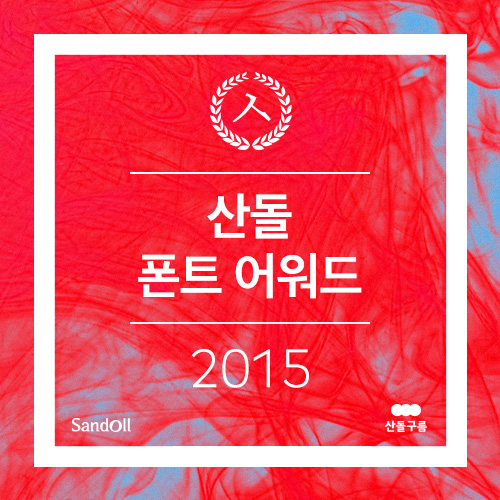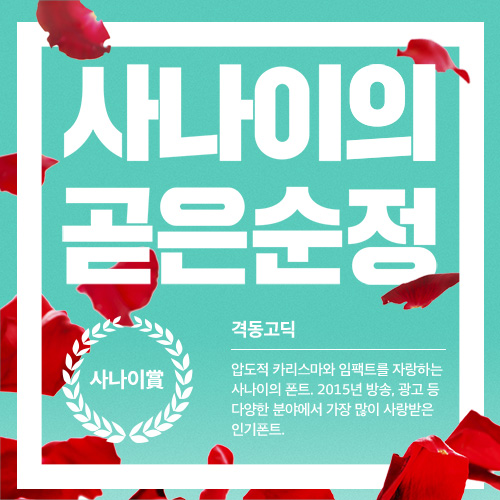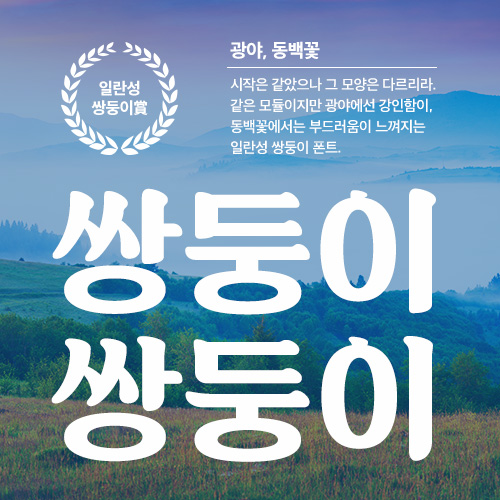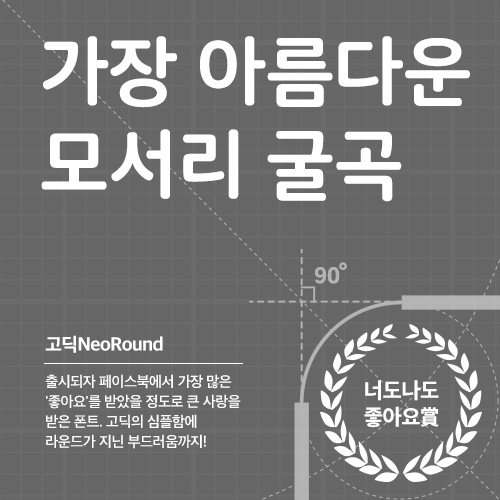
산돌 폰트 어워드 2015 : 당신이 사랑한 폰트들
작년 한 해, 당신이 가장 사랑한 폰트는 무엇인가요?
무심코 쓰다보니 어느새 없으면 안 되는 ‘완소’ 폰트 하나씩은 가지고 계시죠? 산돌 수백 종의 폰트 중에서 2015년에 가장 많이 사랑받았던 폰트를 다음과 같이 골라보았습니다. 이른바, 산돌 폰트 어워드 2015. 그 영광의 수상작들을 만나보시죠.
산돌 폰트 어워드 2015
사나이賞 – 격동고딕
압도적 카리스마와 임팩트를 자랑하는 사나이의 폰트.
2015년 방송, 광고 등 다양한 분야에서 가장 많이 사랑받은 인기폰트
신여성賞 – 개화
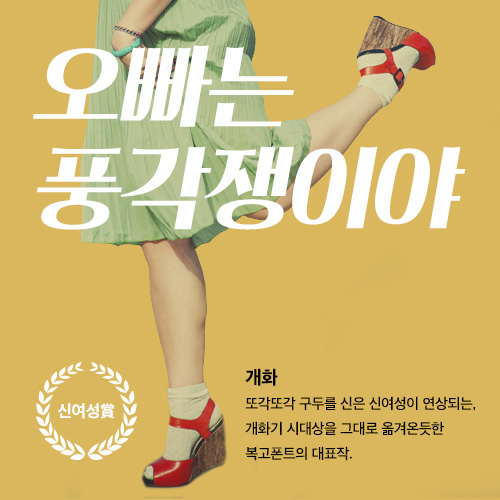
또각또각 구두를 신은 신여성이 연상되는,
개화기 시대상을 그대로 옮겨온듯한 복고폰트의 대표작
일란성 쌍둥이賞 – 광야, 동백꽃
시작은 같았으나 그 모양은 다르리라.
같은 모듈이지만 광야에선 강인함이, 동백꽃에서는 부드러움이 느껴지는 일란성 쌍둥이
여린 소녀賞 – 하이테크
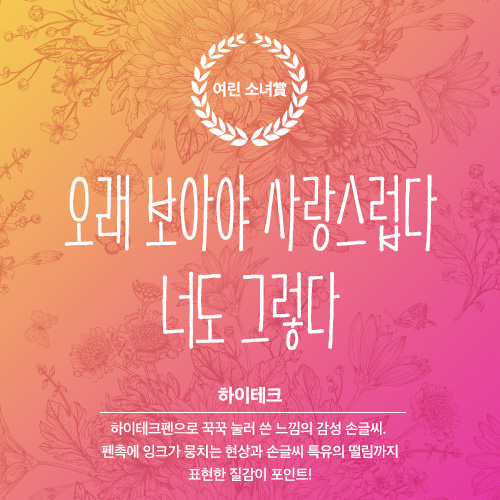
하이테크펜으로 꾹꾹 눌러 쓴 느낌의 감성 손글씨.
펜촉에 잉크가 뭉치는 현상과 손글씨 특유의 떨림까지 표현한 질감이 포인트!
침샘자극賞 – 단팥빵
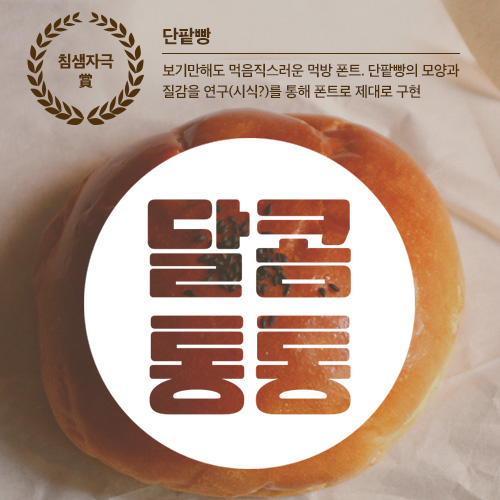
단팥빵 보기만해도 먹음직스러운 먹방 폰트.
단팥빵의 모양과 질감을 연구(시식?)를 통해 폰트로 제대로 구현
콜라보賞 – 스웨거
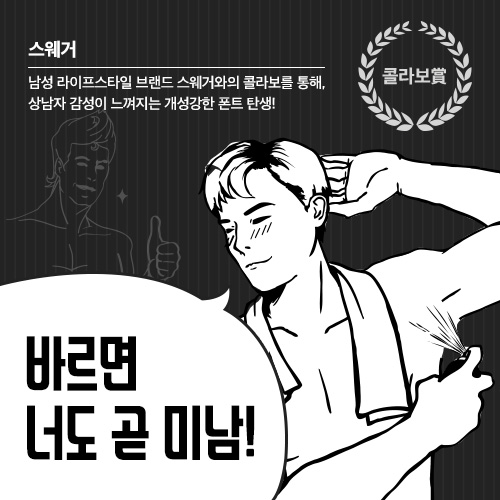
남성 라이프스타일 브랜드 스웨거와의 콜라보를 통해,
상남자 감성이 느껴지는 개성강한 폰트 탄생!
너도나도 좋아요賞 – 고딕네오라운드
출시되자 페이스북에서 가장 많은 ‘좋아요’를 받았을 정도로
큰 사랑을 받은 폰트. 고딕의 심플함에 라운드가 지닌 부드러움까지!
전문가도 인정賞 – 제비2
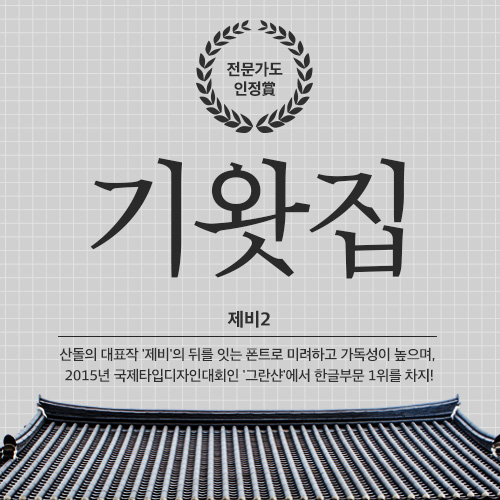
산돌의 대표작 ‘제비’의 뒤를 잇는 폰트로 미려하고 가독성이 높으며,
2015년 국제 타입 디자인대회인 ‘그란샨’에서 한글부문 1위를 차지!